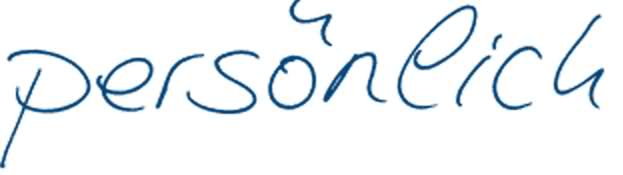
Suche eine Schreib-Schrift-Art kann sie aber nicht finden.
ich suche eine Schreibschrift wie auf dem Foto.
das ist doch handschrift?
schaue dich hier um.
Handschrift ist der Oberbegriff. Blockschrift ist eine etwas genauere Definition.
Blockschrift im Sinne von handgeschriebene Lettern ohne Verbindungsstriche.
Ein nettes Beispiel ist Augie (Freeware):
Die Schriften werden gelegentlich auch in die Rubrik ..Marker'' gesteckt.
So die Schrift 20¢ Marker:
Sehr interessant finde ich den freien ,,Font On a Stick'' von Fontdiner:
Blambot hat eine große Auswahl davon:
Ich suche eigentlich den Namen der Schriftart die auf dem Bild zu sehen ist.